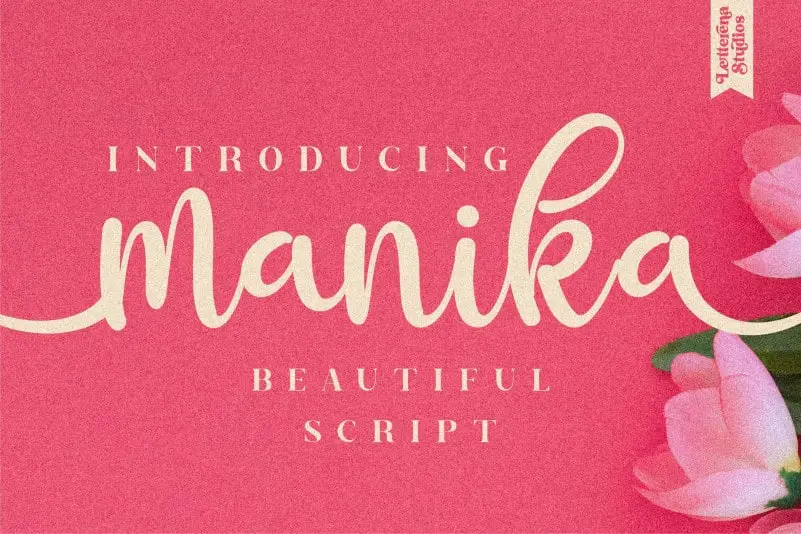
Manika Calligraphy Font – Fonte Grátis
Manika Calligraphy Font
A Manika Calligraphy Font é uma fonte escrita a mão que oferece um toque amigável e encantador. Ela faz parte do amplo catálogo de fonts script disponíveis para designers e criativos digitais. Esta elegante escolha de fontes traz um ar retrô e sofisticado, especialmente adequada para projetos de design gráfico que buscam uma aparição natural e cuidadosamente elaborada. Seja para criar cartões de aniversário delicados, designs de marca ou texturas de letras interessantes para suas produções digitais, a Manika Calligraphy Font é uma escolha perfeita. Que tal incorporar um pouco mais do encanto da escrita a mão em seus projetos?